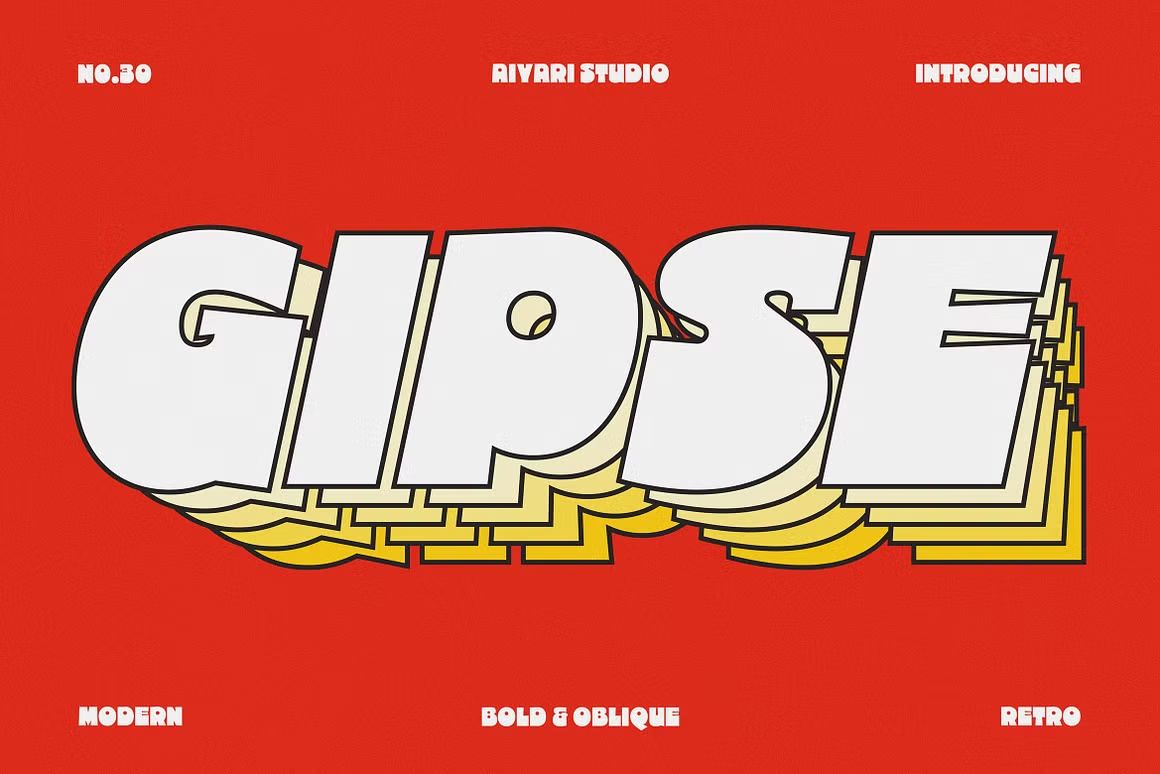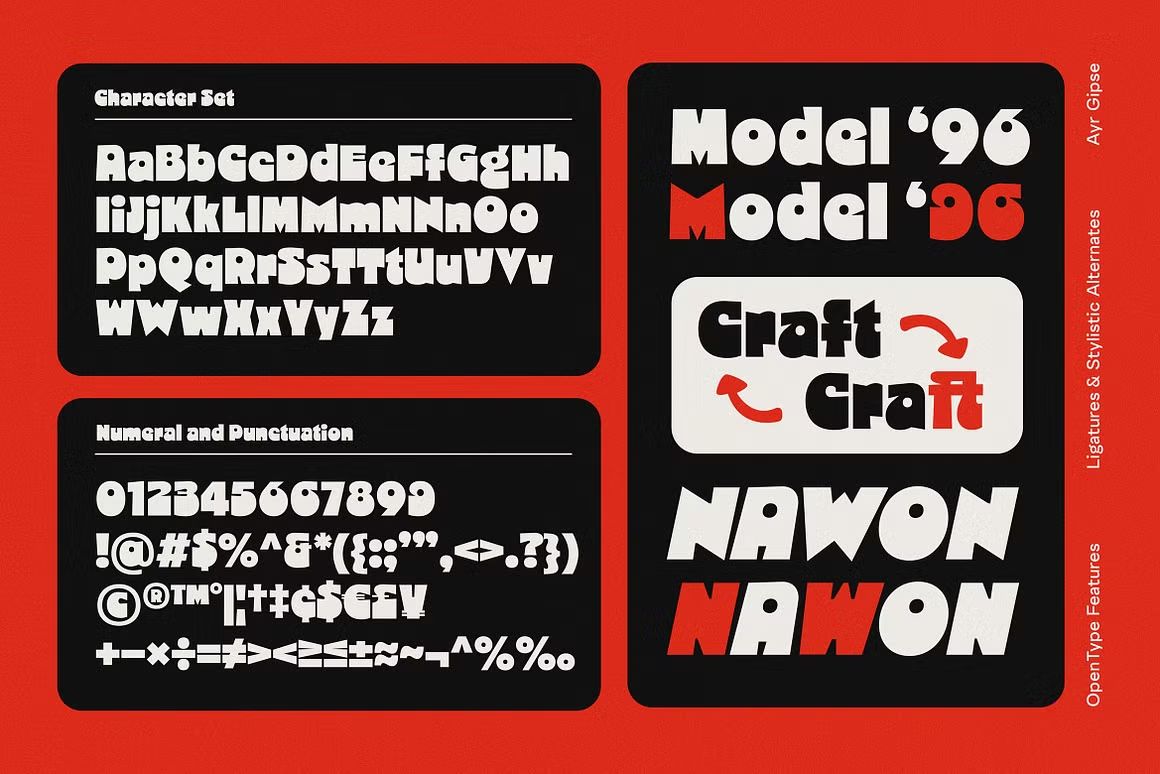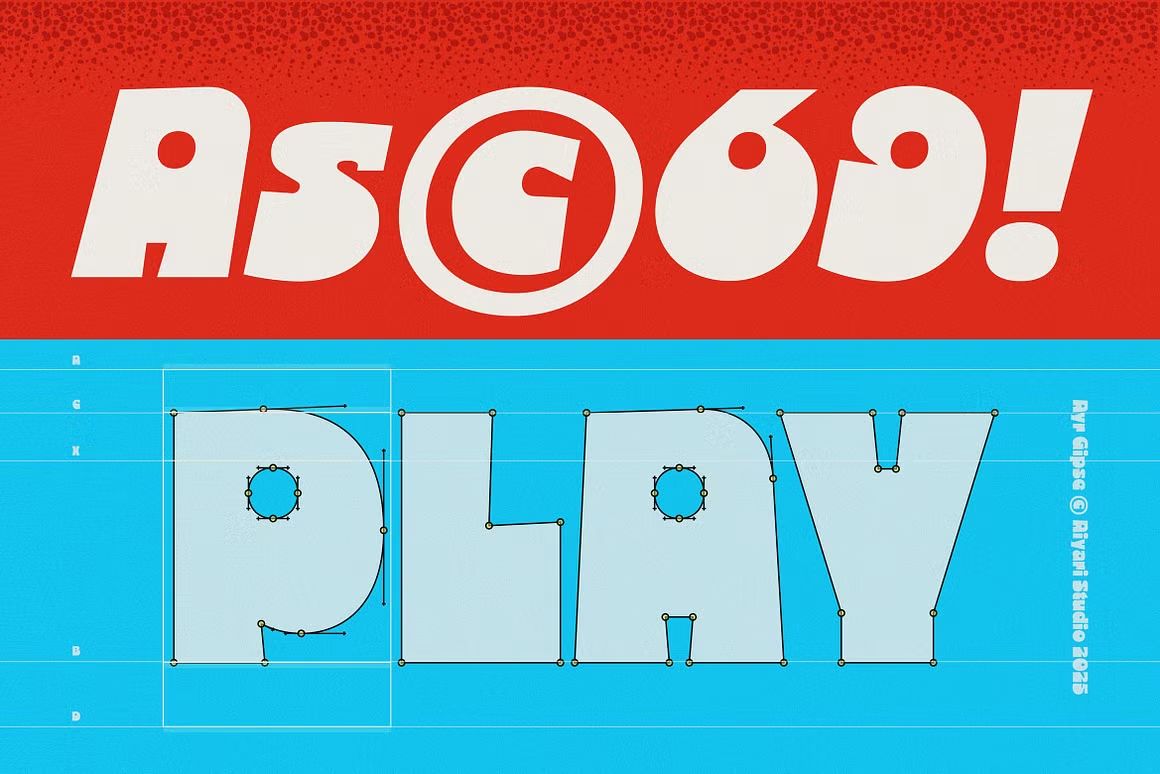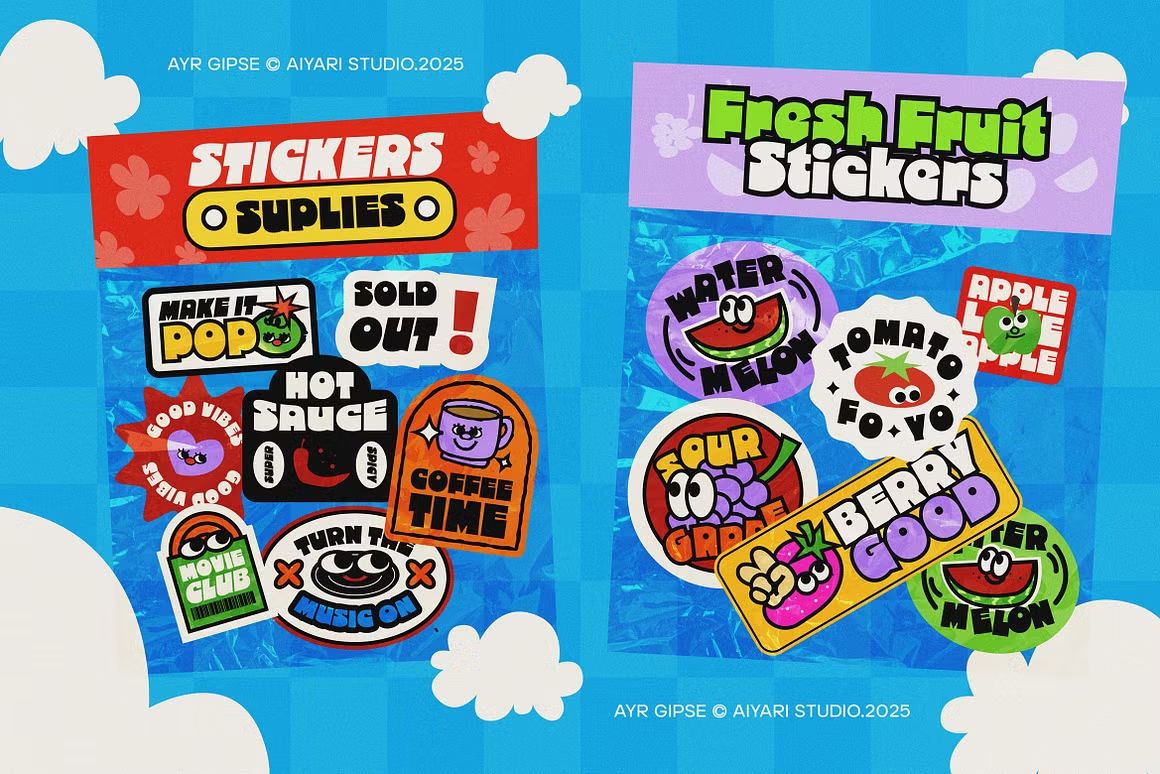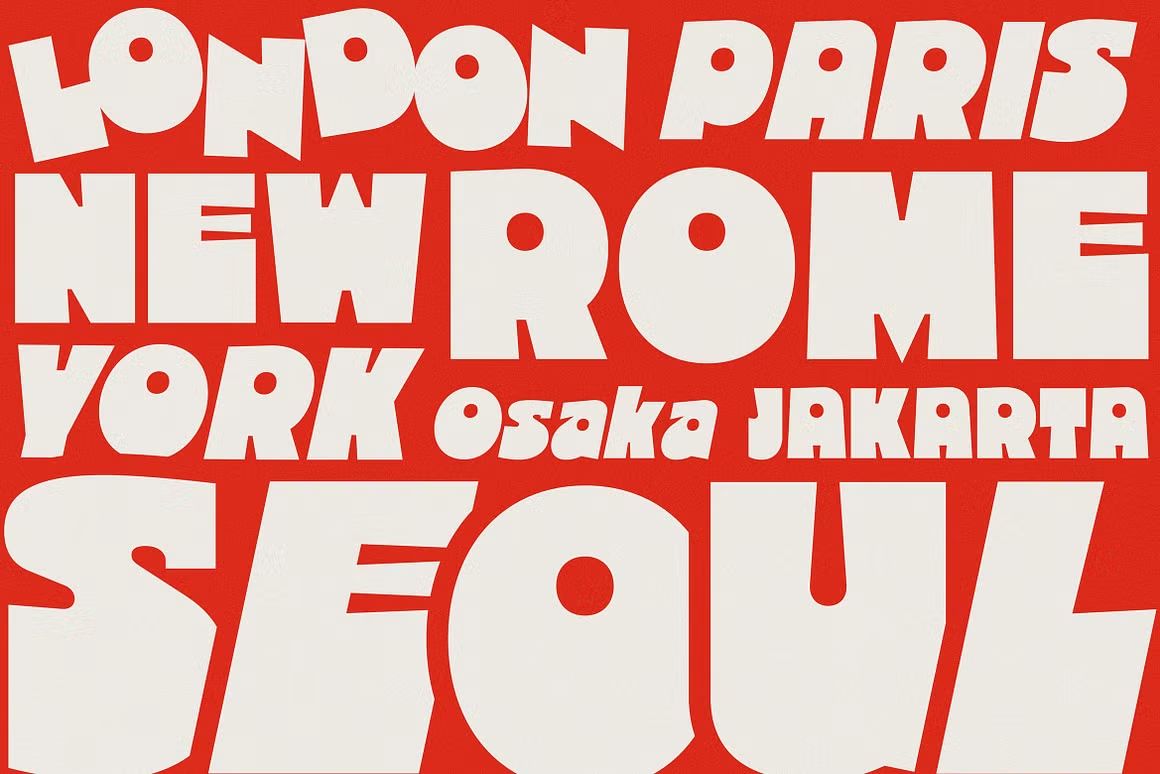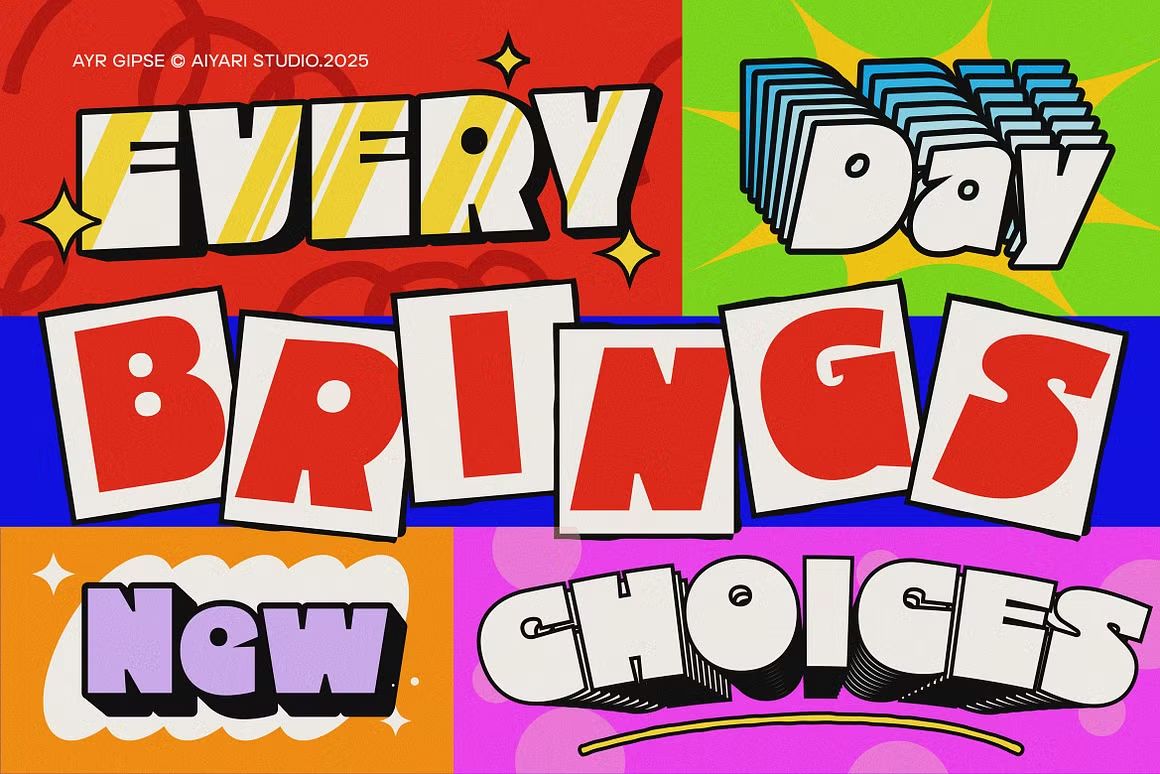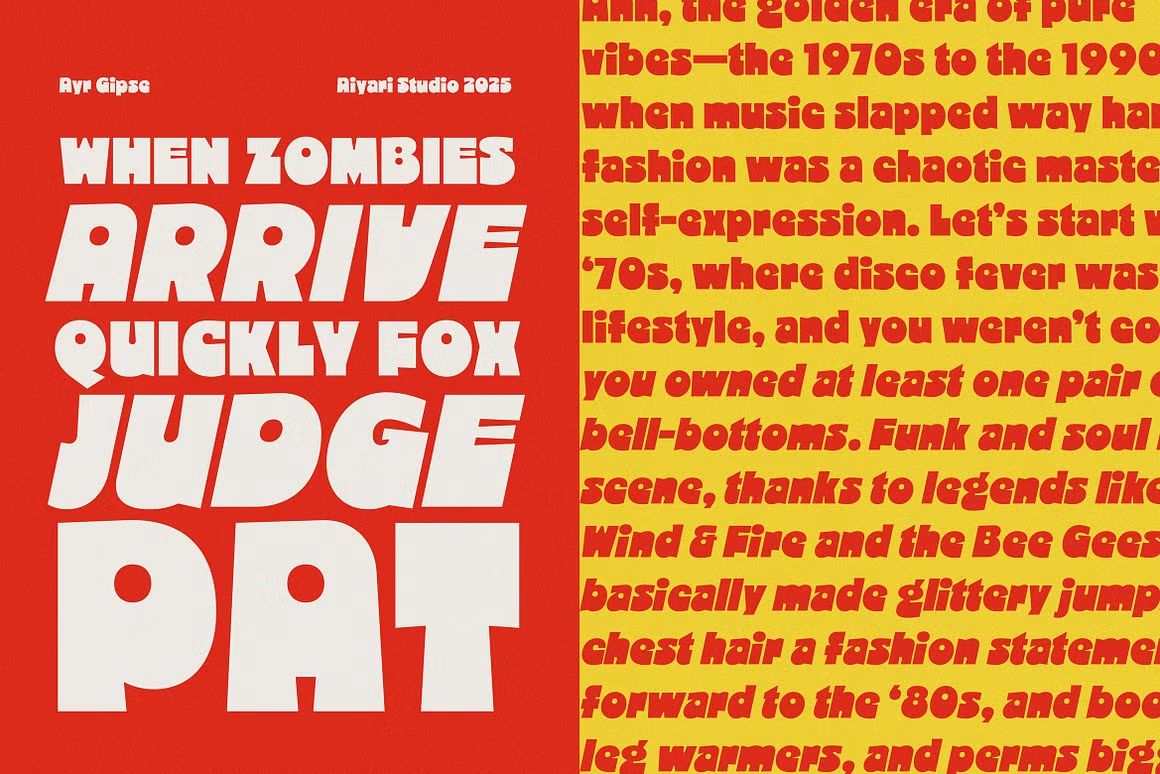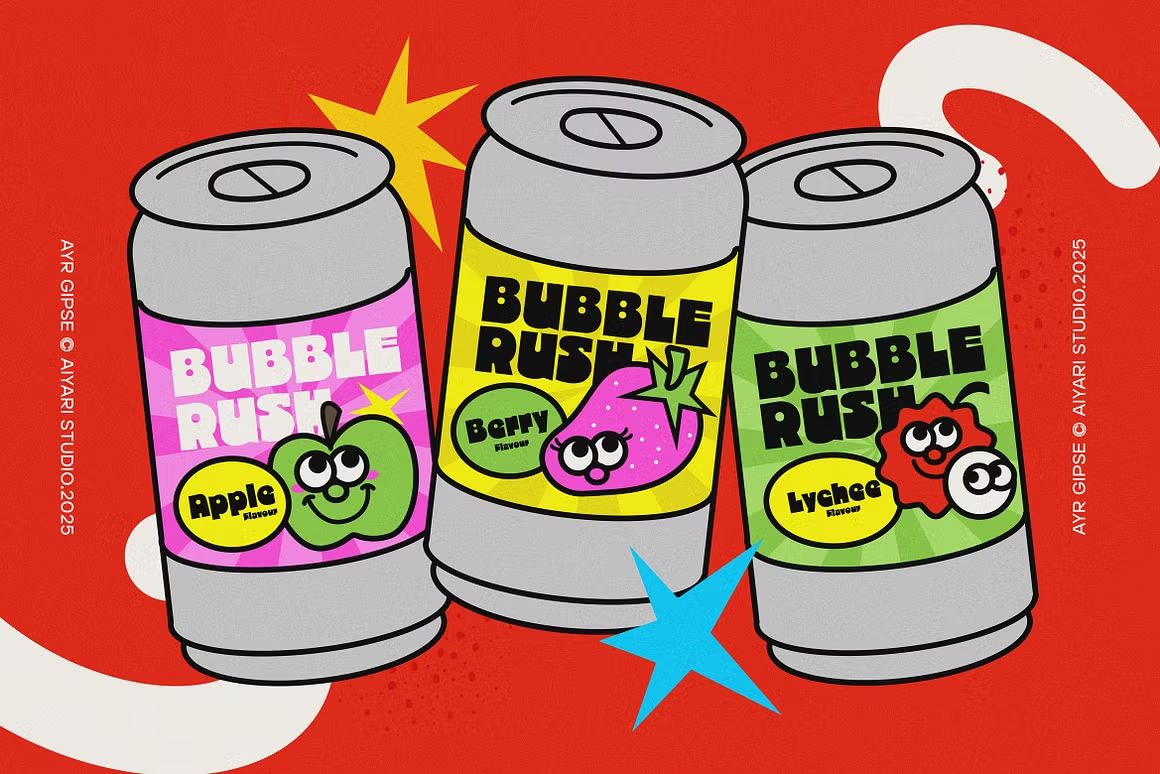
Gipse – Sans Serif Font
Gipse adalah font sans serif bergaya modern dan minimalis dengan bentuk huruf yang bersih, seimbang, dan mudah dibaca. Desainnya yang sederhana namun elegan membuatnya cocok untuk berbagai kebutuhan desain seperti branding, editorial, web design, kemasan produk, dan presentasi profesional. Gipse memberikan tampilan yang fresh, netral, dan serbaguna.
• Sans serif minimalis dengan proporsi seimbang
• Ideal untuk branding, editorial, dan desain digital
• Termasuk huruf kapital, kecil, angka, dan simbol